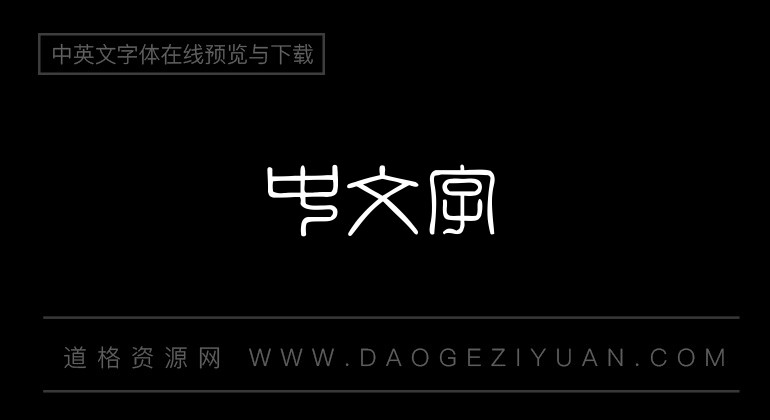
金梅印篆字国际码是一款由美国设计师梅·纳卡里(Mae Nakarri)设计的英文字体,它是一款结合了中国古典篆刻技法和西方印刷技术的英文字体,结合了东西方文化的精髓。字体特点是拥有中国古典篆刻的笔画细腻,线条细腻流畅,字形清晰,笔画比例协调,以及更大的可读性。它可以用于排版、平面设计、印刷出版、网页设计等多种场景,为英文文案增添中国古典文化的气息。文件名:jinmeiyinzuozi.ttf
金梅印篆字国际码是一款非常不错的手写艺术字体,具有很好的视觉感,适合于文化类的宣传设计、商业类品牌的广告和产品包装设计以及个性化文字排版等较多场景。